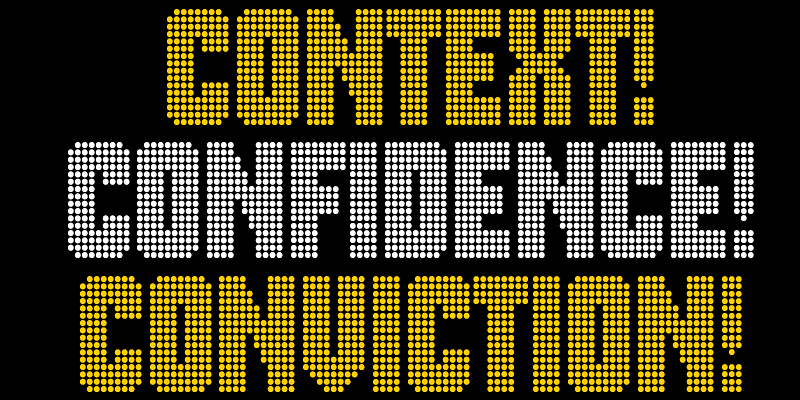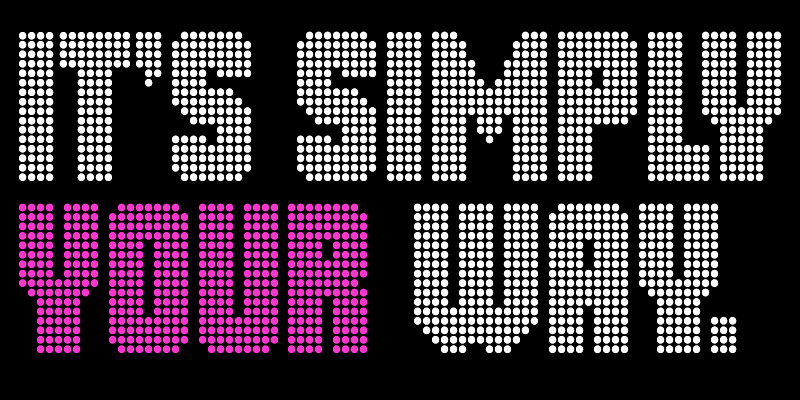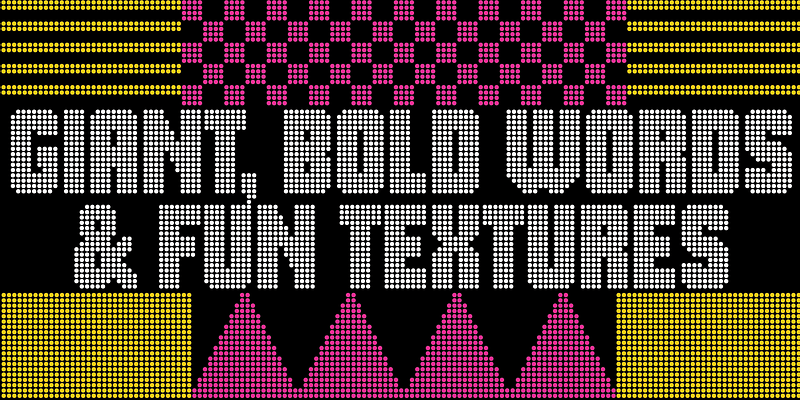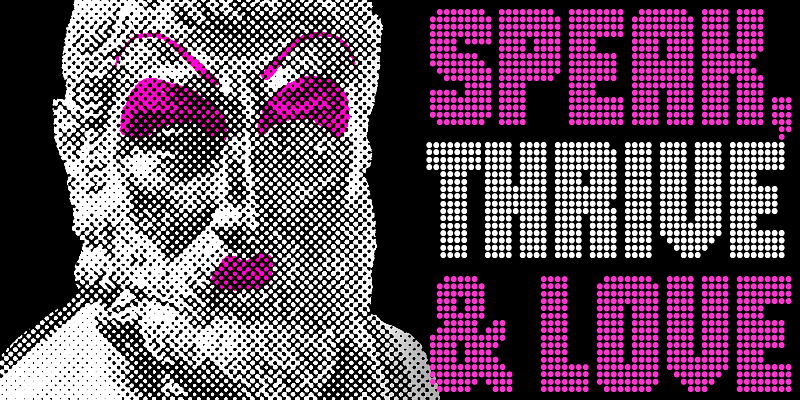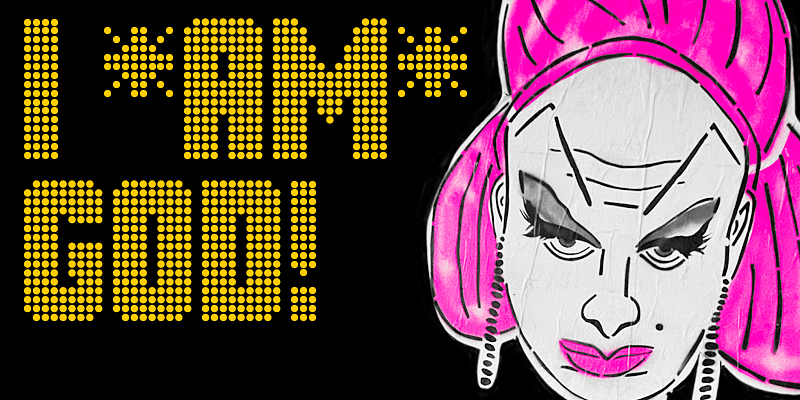
Gloridot은 크고 견고한 헤드라인과 제목을 위한 서체입니다. 디자인은 Dan Rhatigan이 자신의 잡지인 Pink Mince의 발행을 위해 재현하려고 했던 오래된 잡지 표지의 서체에서 나온 몇 개의 글자로 시작되었습니다. 영광스러운 몇 가지 문자를 형성한 점들의 격자는 처음에는 알파벳을 구성하는 단순한 시스템처럼 보였으나, 이 시스템이 약 505개 언어와 더불어 테두리와 패턴을 만드는 데 사용할 수 있는 기호들을 지원하는 서체로 확장되면서 매혹적인 퍼즐로 성장했습니다.